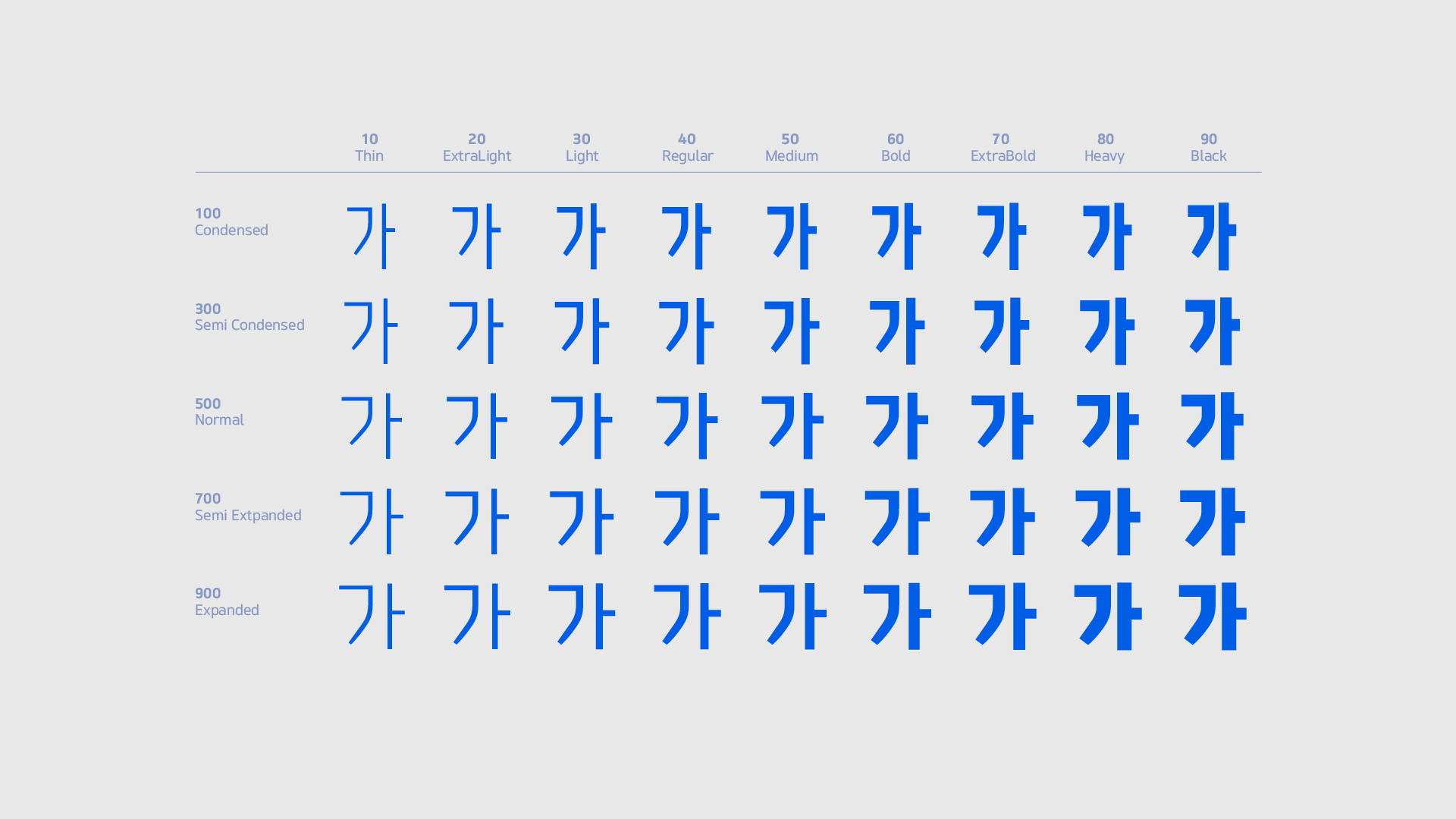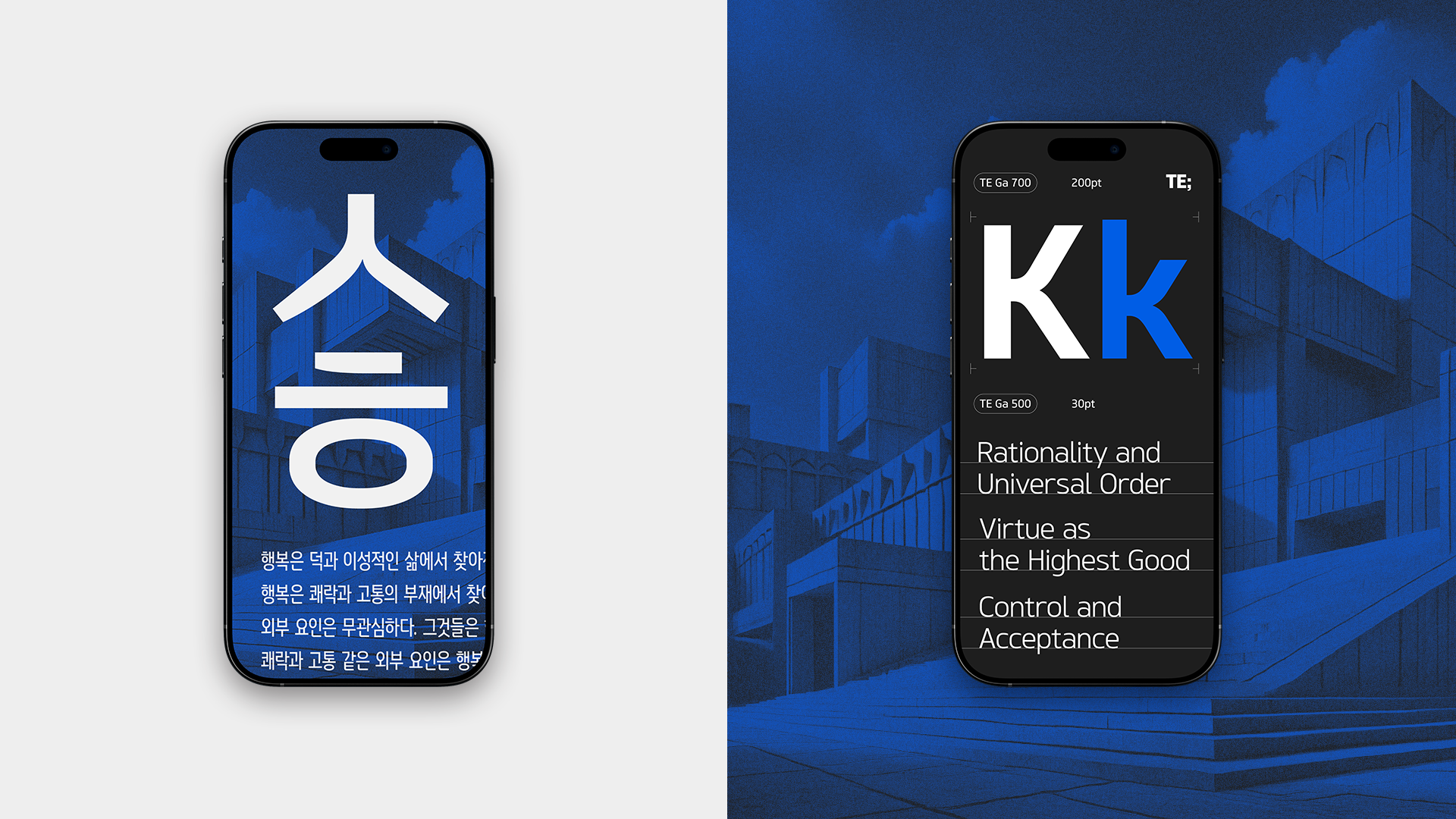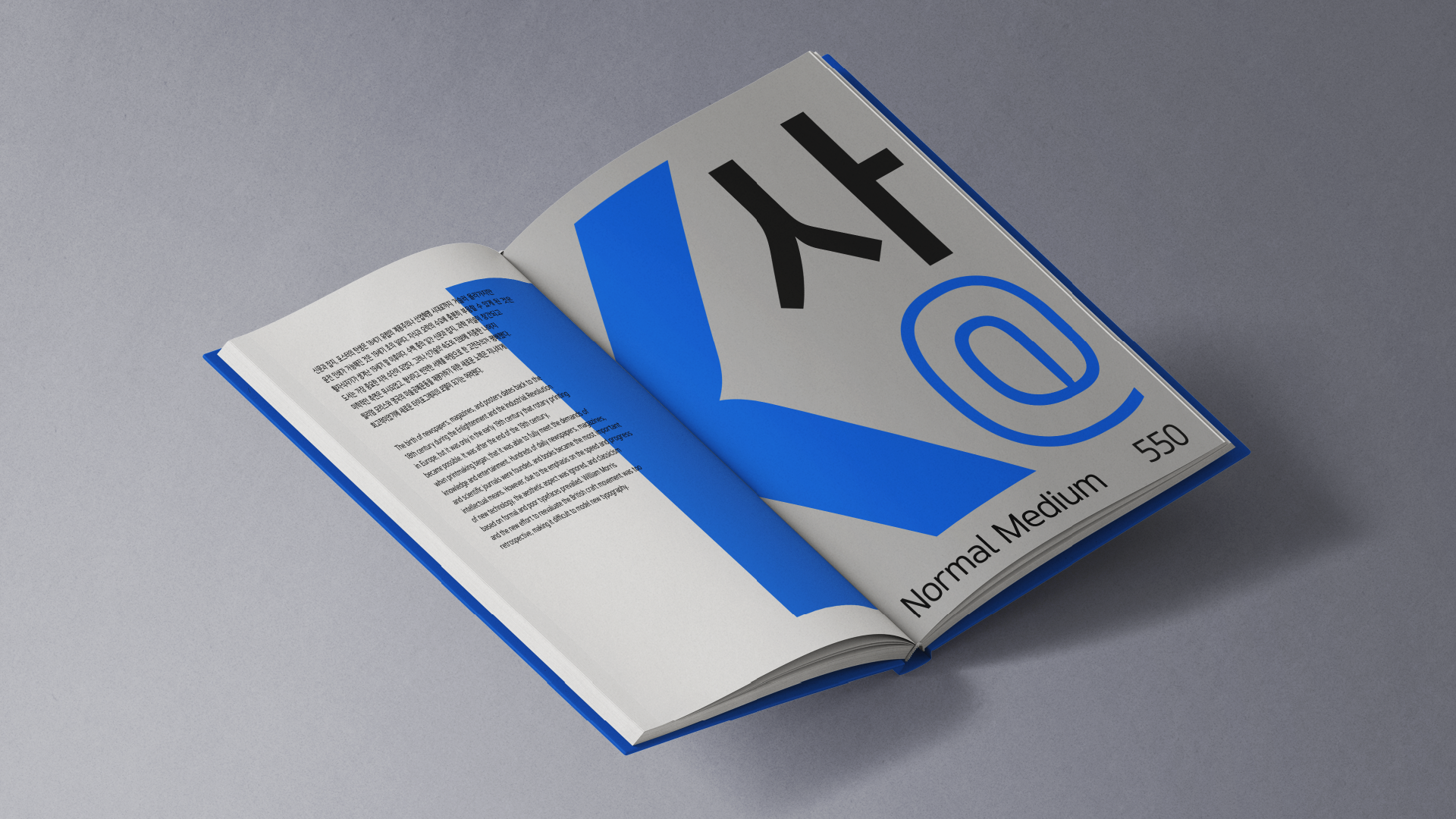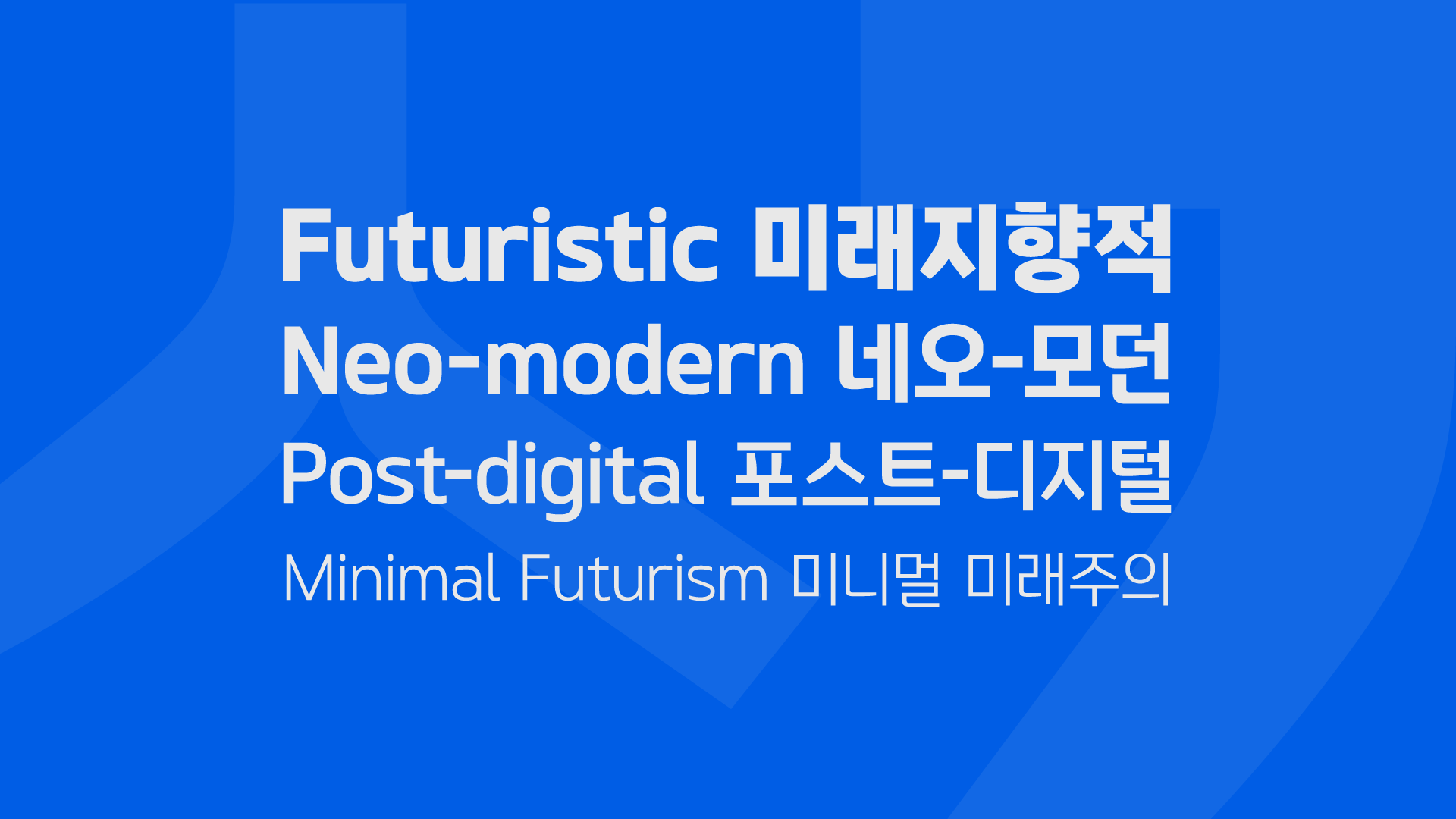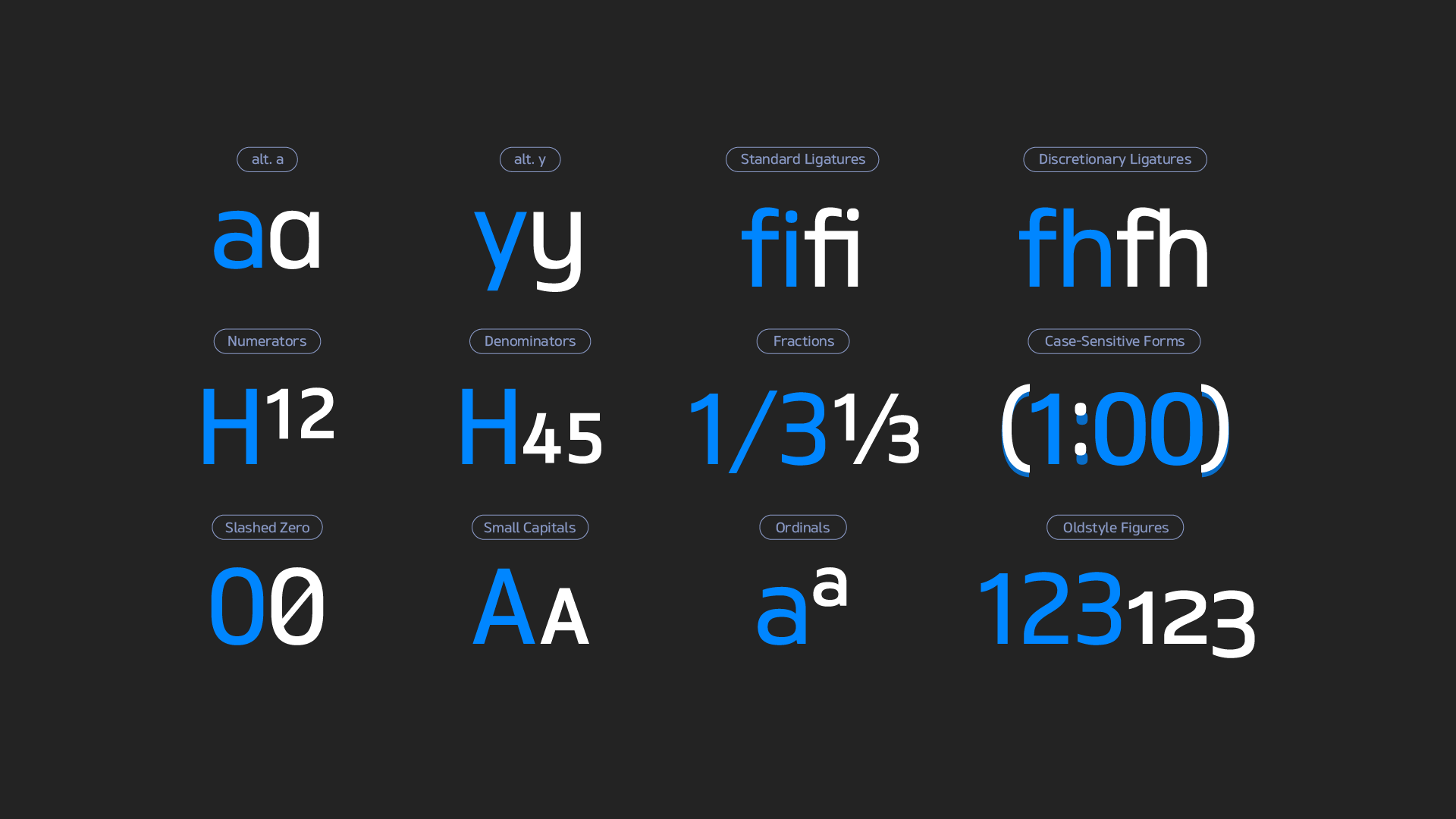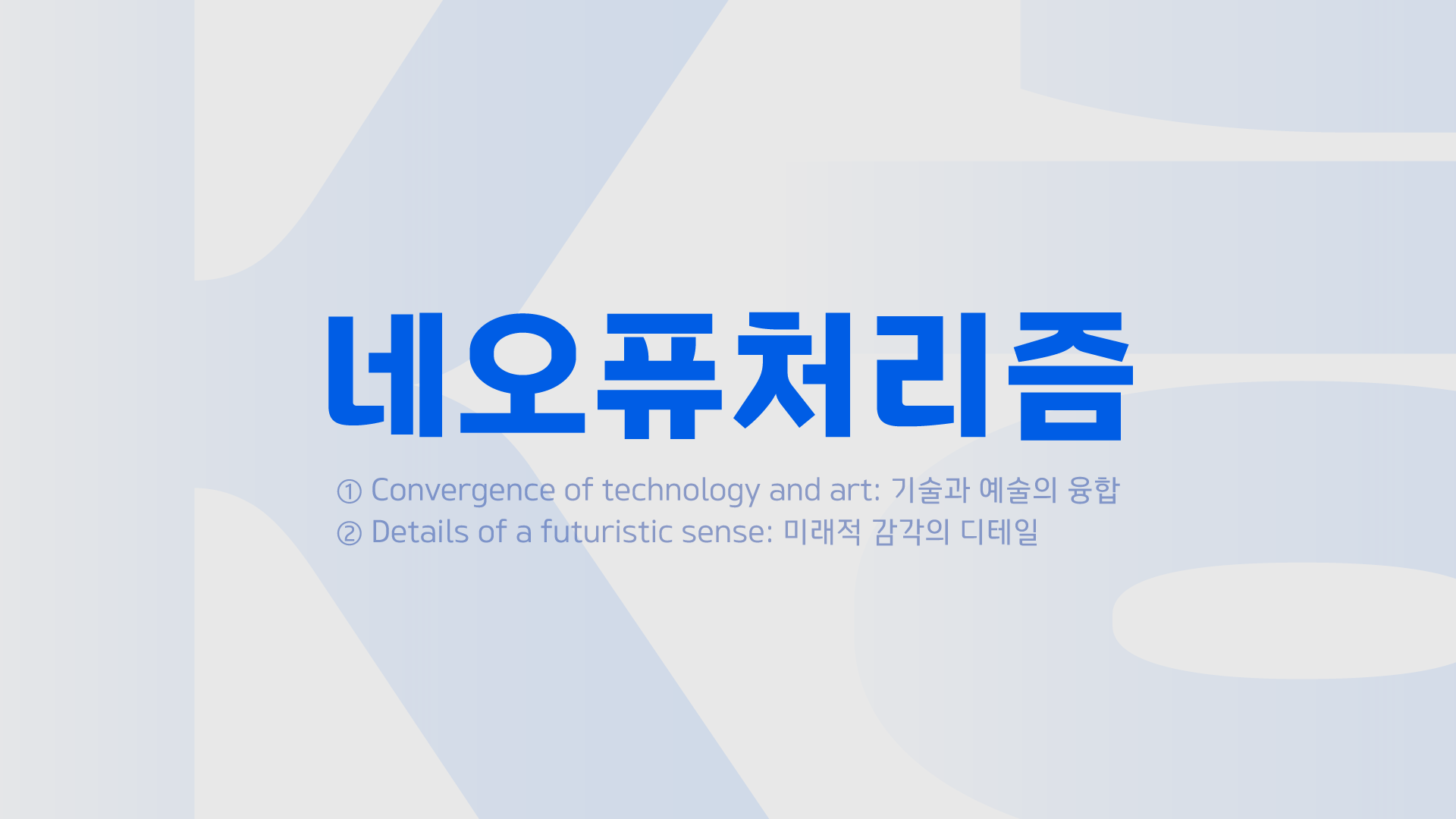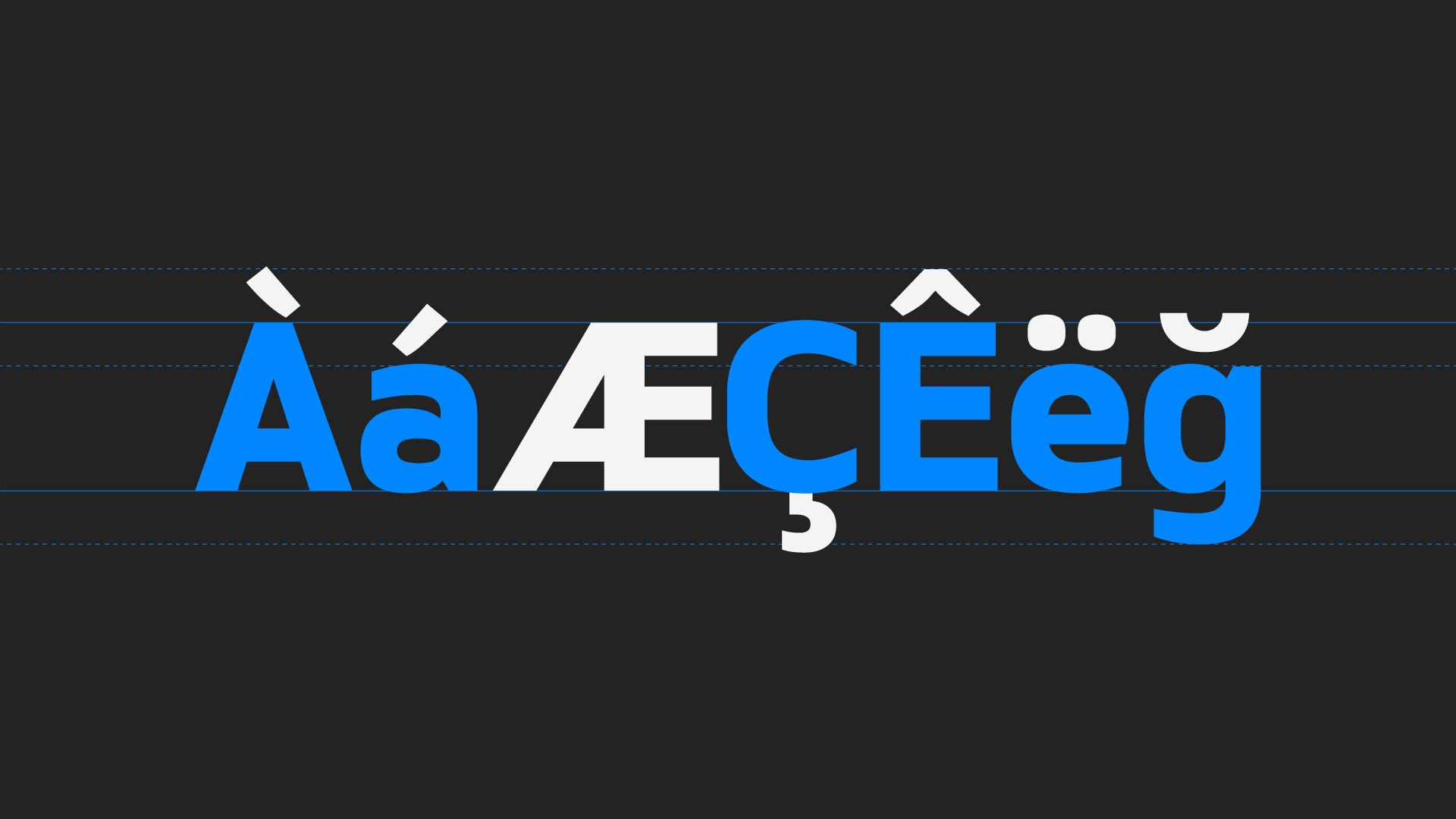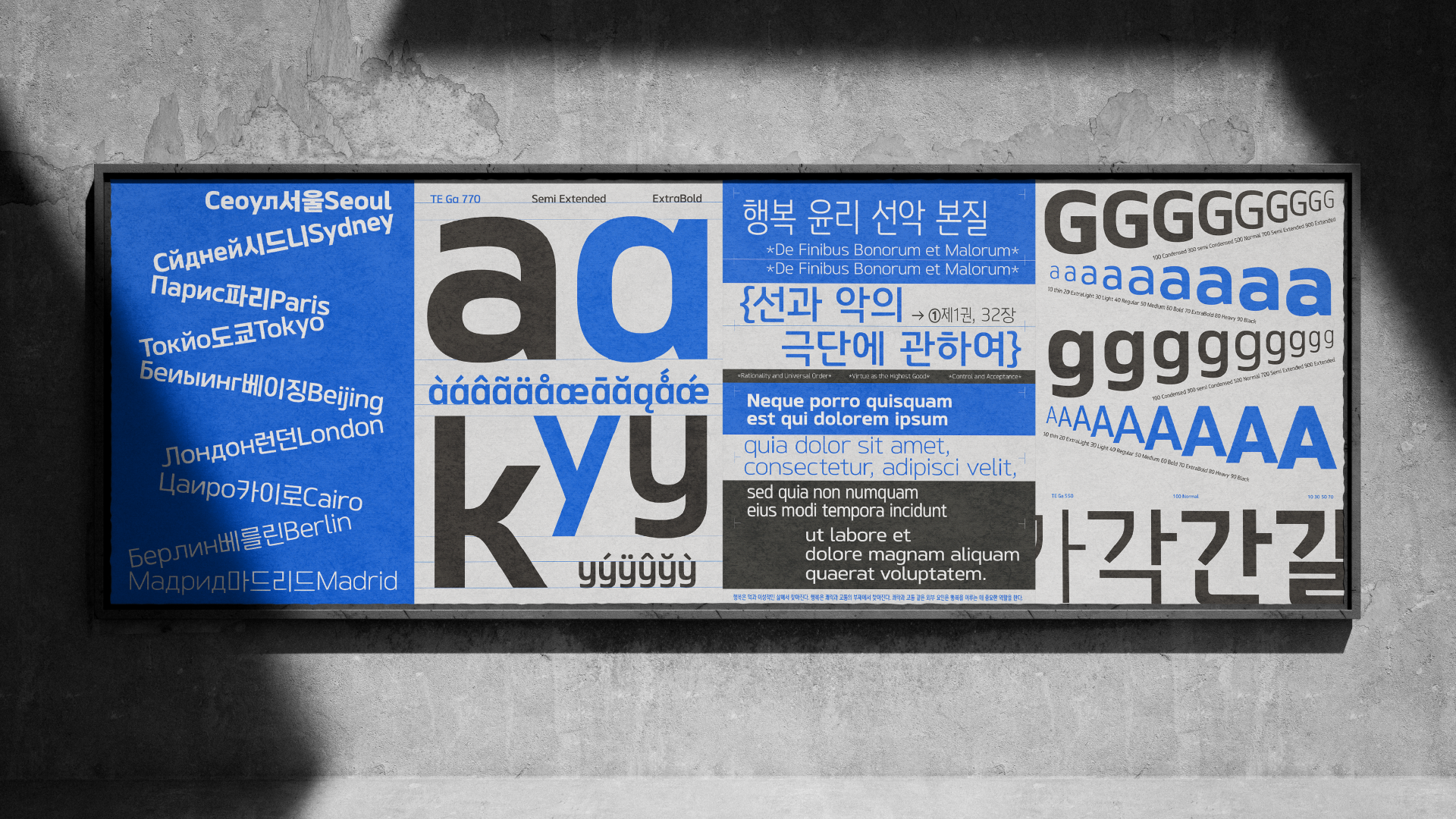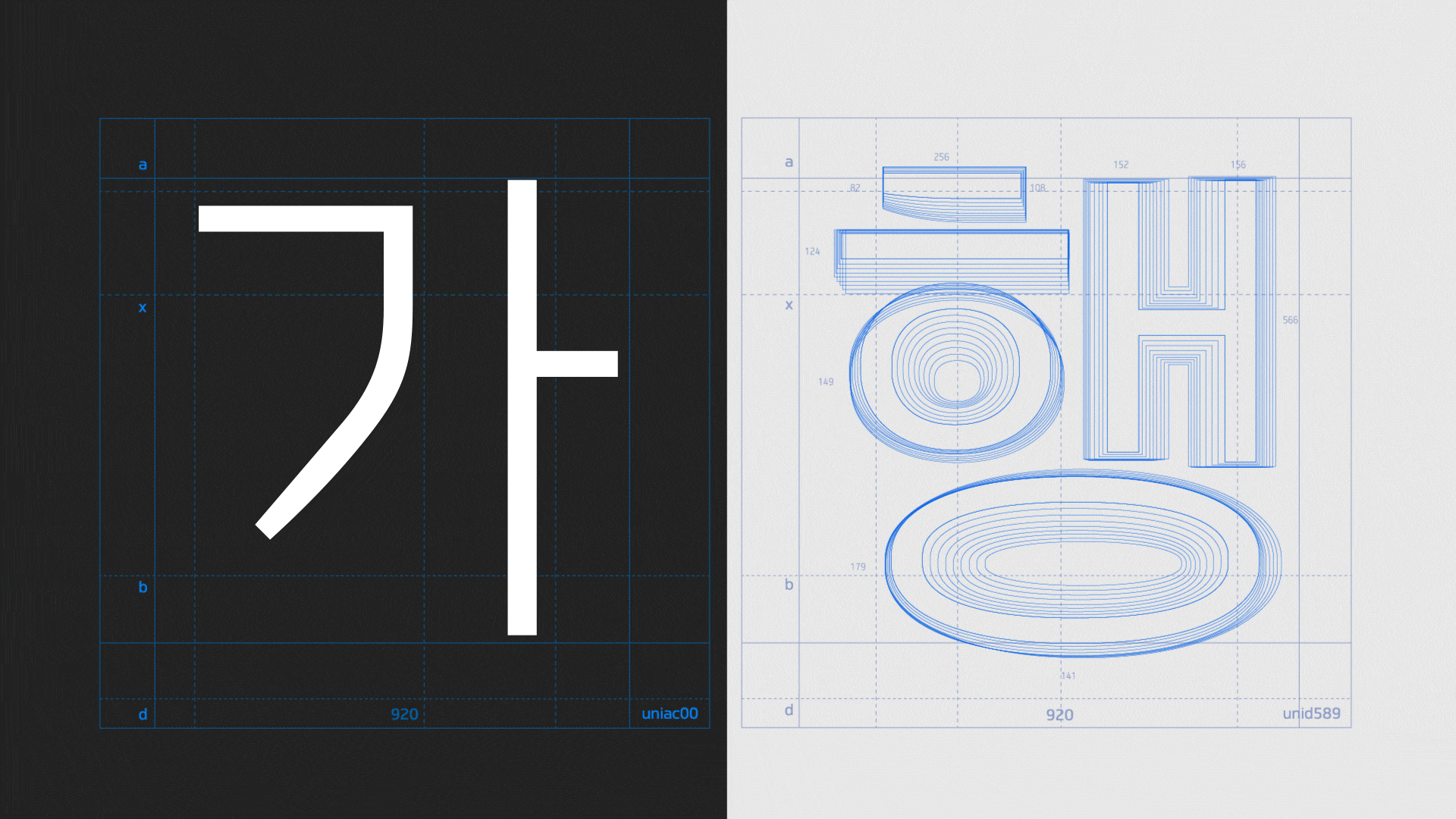
TE 가 패밀리는 명료하고 심플하며 가독성이 높은 미래적인 네오-모던 산세리프 서체입니다. 이 서체 패밀리의 글자는 장식적인 요소 없이 기하학적인 모양으로 디자인되었습니다. 또한 개별 글자 형태 사이의 간격을 정밀하게 조정하여 완벽한 서체를 만들었습니다.
TE 가 패밀리는 명료하고 심플하며 가독성이 높은 미래적인 네오-모던 산세리프 서체입니다.
이 서체 패밀리의 글자는 장식적인 요소 없이 기하학적인 모양으로 디자인되었습니다.
또한 개별 글자 형태 사이의 간격을 정밀하게 조정하여 완벽한 서체를 만들었습니다.
서체 이름
서체 종수
글자수
제작년도
오픈타입
TE 가
45종 (5자폭* 9굵기)
한글 11,172자, 영문 Basic Latin 95자, 라틴확장 330자,
KS심볼 986자, 대체글립 141자
2025
aalt, case, dlig, dnom, frac, kern, liga, numr, onum, pnum,
sinf, sups, tnum, zero, smcp, salt
출시년도
한글 11,172자, 영문 Basic Latin 95자, 라틴확장 330자, KS심볼 986자, 대체글립 141자
aalt, case, dlig, dnom, frac, kern, liga, numr, onum, pnum, sinf, sups, tnum, zero, smcp, salt